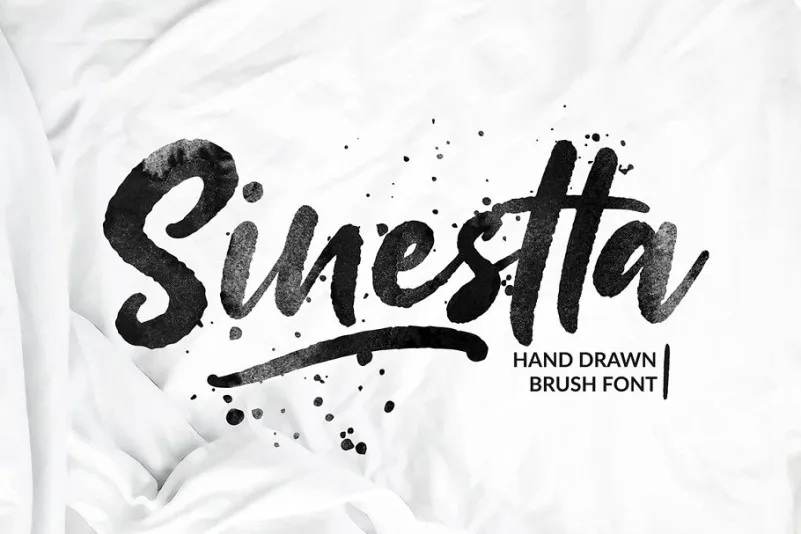
Sinestta Brush Font – Download Grátis
A fonte Sinestta Brush Font é uma escolha perfeita para quem procura uma fonte script casual e divertida. Ela foi criada com as delicadas tocas de um pincel feito à mão, tornando-a ideal para adicionar um toque autêntico e quase imperfeito de escrita a qualquer projeto. Esta font é perfeitamente compatível com uma variedade de usos, como assinaturas, logotipos, festas e publicidade, além de ser uma ótima escolha para criações em papel, como capas de livros e embalagens. Além disso, a Sinestta Brush é uma excelente fonte para se inspirar nas criações de arte digital, incluindo títulos para posters, banners publicitários, ilustrações e até mesmo cartões de agradecimento. Suas características de ponta aberta permitem que você crie obras de arte criativas e autênticas que têm o aspecto de se ter sido escritos por si mesmo, sem a necessidade de usar técnicas complexas ou ferramentas especializadas. Com sua elegante aparência e toques naturais de pincel, é impossível não sentir-se chamado para experimentar essa fonte inovadora e versátil.